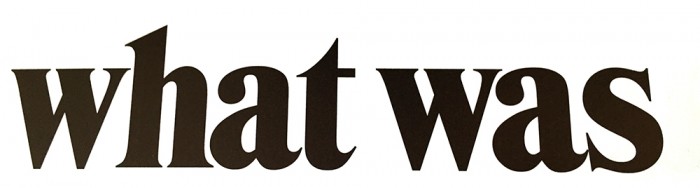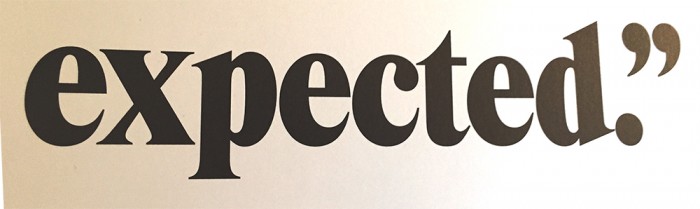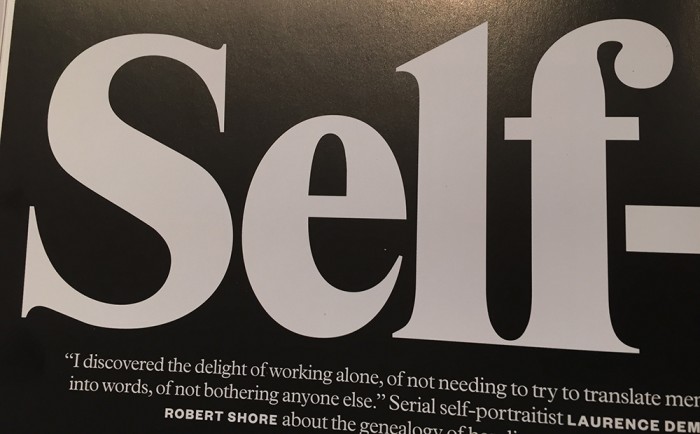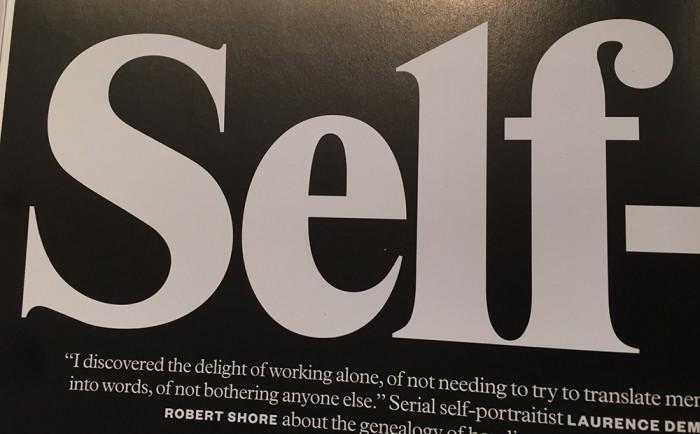
Suche Schrift (expected)
Wer kann mir helfen? Dachte erst etwas Richtung Bodoni aber es passt alles nicht :-/
Nee, ganz grob geht das eher in Richtung einer fetten Times. Times New Roman ist dicht dran, wobei ihr ein paar Schrägen fehlen. Abziehen bei der Betrachtung musst Du außerdem die Verzerrung Deines Beispiels.
Nur mal zum Vergleich:
Das schaut sehr nach der Times Modern aus. Den meisten dürfte sie von Suhrkamps ›Taschenbuch Wissenschaft‹ bekannt sein.
Danke euch schon einmal! Es scheint wirklich eine Times zu sein – hätte ich nie gedacht. So ganz passt es nur mit dem «f» noch nicht...
Das ist die Schrift, die als Headline-Typo und wohl auch im Fließtext im elephant-magazine verwendet wird
So ganz passt es nur mit dem «f» noch nicht...
Wie ich sagte: Times Modern von Elsner + Flake. Da passt auch das f.